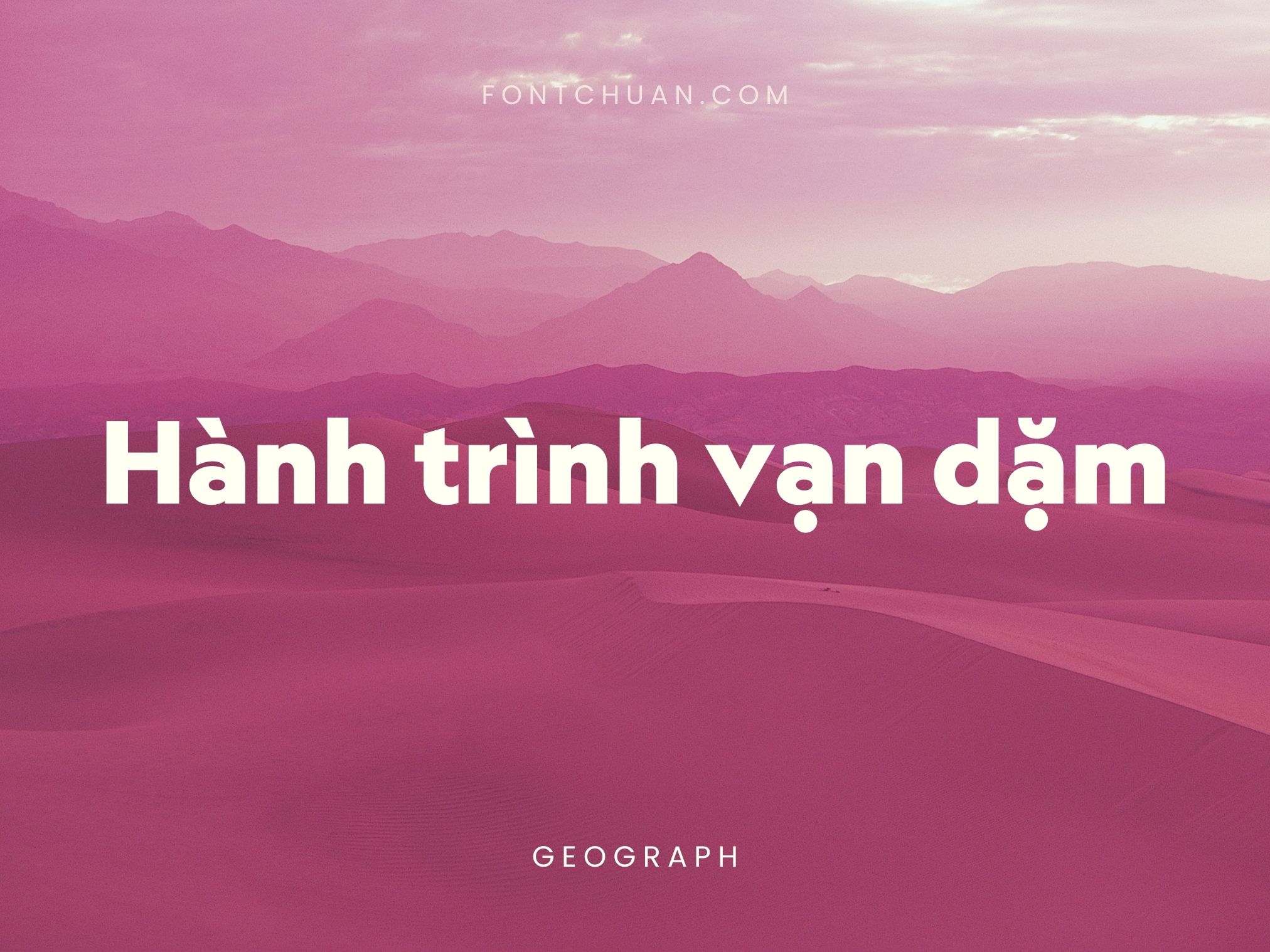
Font Geography Việt Hóa
Geograph là một font chữ sans-serif hình học hiện đại, được thiết kế bởi Kris Sowersby và phát hành bởi Klim Type Foundry. Ban đầu, font này được tạo ra cho National Geographic, kết hợp giữa lý tưởng của Futura và tính thực dụng của Super Grotesk. Với bộ ký tự thay thế đa dạng, Geograph cho phép tạo ra các kết cấu và tông màu typographic linh hoạt. Font này được sưu tầm và đăng bởi thành viên của Font Chuẩn, hỗ trợ tiếng Việt và nhiều ngôn ngữ khác.
Geograph có cấu trúc chữ rõ ràng, độ dày đều và các đường nét tinh tế, tạo nên sự cân bằng giữa tính thẩm mỹ và khả năng đọc. Font này phù hợp cho các thiết kế tạp chí, poster, tiêu đề và nhận diện thương hiệu. Đồng thời, Geograph cũng có thể được sử dụng như một Font chữ ẩm thực, giúp các nhà hàng, quán ăn và thương hiệu thực phẩm tạo ra sự hiện đại, tinh tế và thân thiện trên menu, bao bì sản phẩm hoặc các ấn phẩm quảng cáo. Ngoài ra, font vẫn được tận dụng hiệu quả trong các ngành quảng cáo, công nghệ, bất động sản, giáo dục, cũng như các sự kiện như lễ hội, sinh nhật, ngày nhà giáo và Valentine.